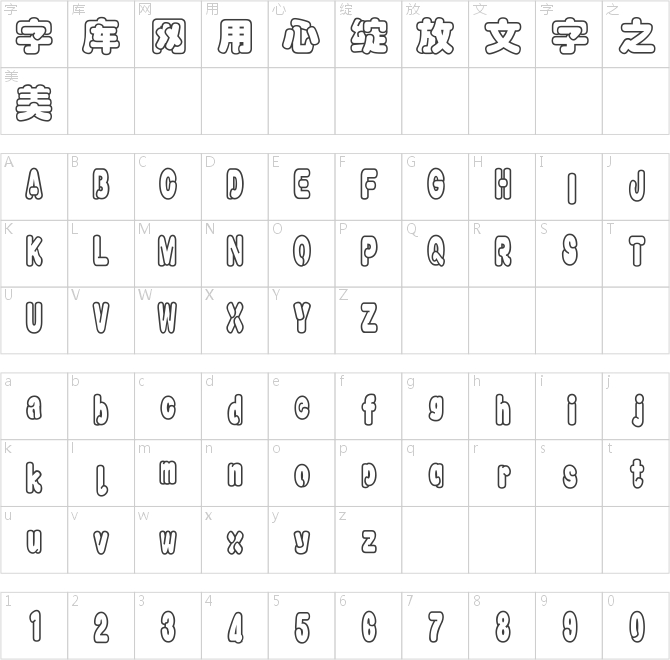
字體名稱: 文鼎彩云簡繁
文鼎彩云簡繁
文鼎彩云的簡體和繁體以及big5合并形成的,二次修訂時補全了原big5的漢字,兼容新版win10
更新Power TrueType Version 5.0版,和原Power TrueType Version 4.0或Power TrueType Version 4.5版本相比又將原Power TrueType big5的擴展471個外字集的部分沒有映射字碼點的漢字進行了對號入座,并修復『?』字誤映射到『抝』字位置的錯誤。
20220120更新Power TrueType Version 5.5版:添加日語當用漢字。一共16721個漢字。
20220204更新:修正「爲」「僞」分別顯示為「為」「偽」的錯誤。
文鼎彩云簡繁字體文鼎空疊圓簡繁字庫是一款讓人賞心悅目、百看不厭的中文字體,適合各類廣告和產品包裝設計應用,字體大小18.49MB,格式為ttf字體,上傳用戶是伊寧,作者/版權方為文鼎字庫